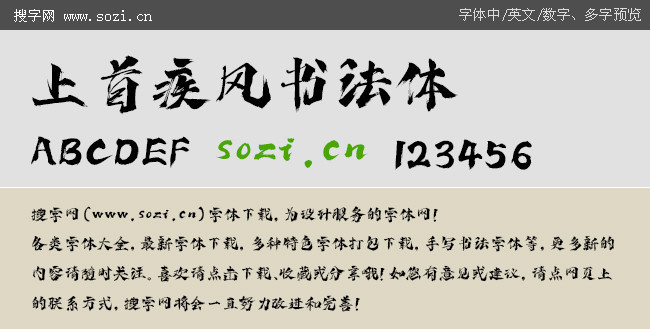
上首疾風(fēng)書法體
搜字網(wǎng)給大家提供一款上首疾風(fēng)書法體中文字體下載,上首疾風(fēng)體,字體風(fēng)格銳利,鈍點(diǎn)強(qiáng)力,夸張的筆鋒增添了字體的活躍性,而且字體中粗細(xì)銜接,使字體顯得生動。適用于搭配標(biāo)志、廣告標(biāo)語、商業(yè)廣告等高端屬性。